그래피티 클래식
Graffiti Classic은 이름에서 알 수 있듯이 정돈되고 균일한 서체로 거리 그래피티의 날것 그대로의 에너지를 발산하는 서체입니다. 그들에게 전문적인 모습. Figma에 낙서 글꼴을 사용할 수도 있습니다.
이 글꼴은 브루클린 기반의 그래피티 아티스트가 지하철 터널과 공책에 태그를 달던 어린 시절에서 영감을 얻어 만들었습니다. 결과 글꼴은 그래피티 레터링의 역동적인 움직임과 리듬을 캡처하여 뚜렷한 서체 품질을 갖습니다.
Graffiti Classic의 눈에 띄는 기능 중 하나는 세심한 간격입니다. 각 문자는 글자 자체의 불규칙한 모양과 형태에도 불구하고 단어와 구가 매끄럽게 흐르도록 신중하게 간격을 둡니다. 디테일에 대한 이러한 관심은 로고에서 포스터, 소셜 미디어 그래픽에 이르기까지 모든 디자인 프로젝트에서 쉽게 사용할 수 있습니다.
나이트페이트
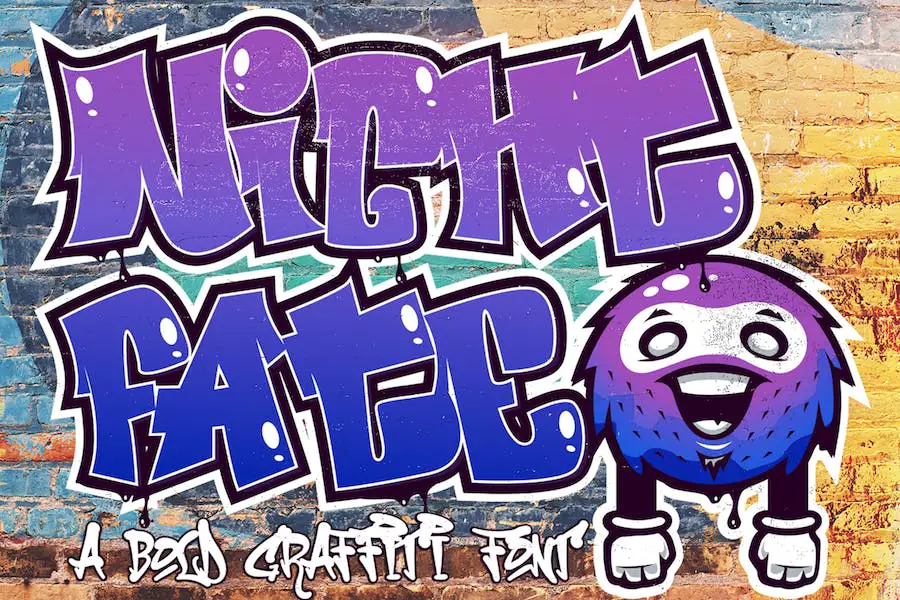
Nightfate 글꼴에서는 특이한 그래피티 같은 모양과 눈에 띄고 프로젝트의 매력을 높일 수 있는 독특한 스타일을 결합하여 프로젝트에 독특한 터치를 추가할 수 있습니다. 그것의 많은 용도 중에는 의류 디자인, 광고, 벽 장식, 공예 등이 있습니다.
Nightfate의 눈에 띄는 특징 중 하나로, 보는 사람의 시선을 확실히 사로잡는 대담하고 엣지 있는 모습은 가장 매력적인 특징 중 하나입니다. 또한 프로젝트 요구 사항과 관련하여 다재다능하기 때문에 이 글꼴을 다양한 용도로 사용할 수 있습니다.
디자인을 한 단계 업그레이드하려는 경우 Nightfate 글꼴을 고려해 볼 가치가 있습니다. 멋진 모양과 개인화된 느낌을 특징으로 하는 이 글꼴은 보는 사람에게 깊은 인상을 남길 것입니다. 시도해 보고 다음 프로젝트의 품질을 어떻게 높일 수 있는지 확인하는 것이 좋지 않습니까?
도시 태그
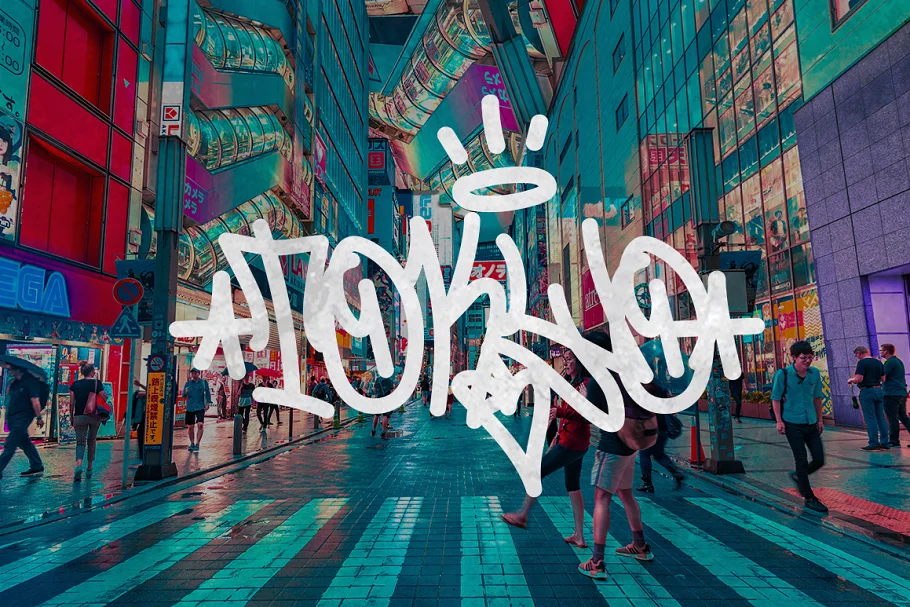
Urban Tags는 그래피티 글꼴로 상징적인 둥근 팁 마커 스타일을 디자인에 적용하여 진정한 스트리트 아트 터치를 선사합니다. 그래피티 씬에 실제 경험이 있는 사람으로서 이 글꼴은 태깅의 본질을 완벽하게 포착했다고 말할 수 있습니다.
Urban Tag를 독특하게 만드는 것은 짧은 공백 문자로 그래피티 스타일의 사실성을 향상시킵니다. 커닝은 일반 글꼴처럼 설정할 수 없으므로 최상의 결과를 얻으려면 커닝을 수동으로 조정해야 합니다. 그러나 최종 결과를 보았을 때 그 노력은 그만한 가치가 있기 때문에 단념하지 마십시오.
이 글꼴은 포스터 및 소품과 같은 디자인 프로젝트에 힙합 또는 거리 예술 감각을 추가하는 데 적합합니다. 엣지있는 음악 앨범 커버부터 도시적인 패션 브랜딩까지 다양한 세팅에 활용될 만큼 활용도가 높습니다. 당신은 문신 예술의 팬입니까? 그렇다면 문신에 그래피티 글꼴을 사용했는지 확인할 수 있습니다.
그래피티 어반
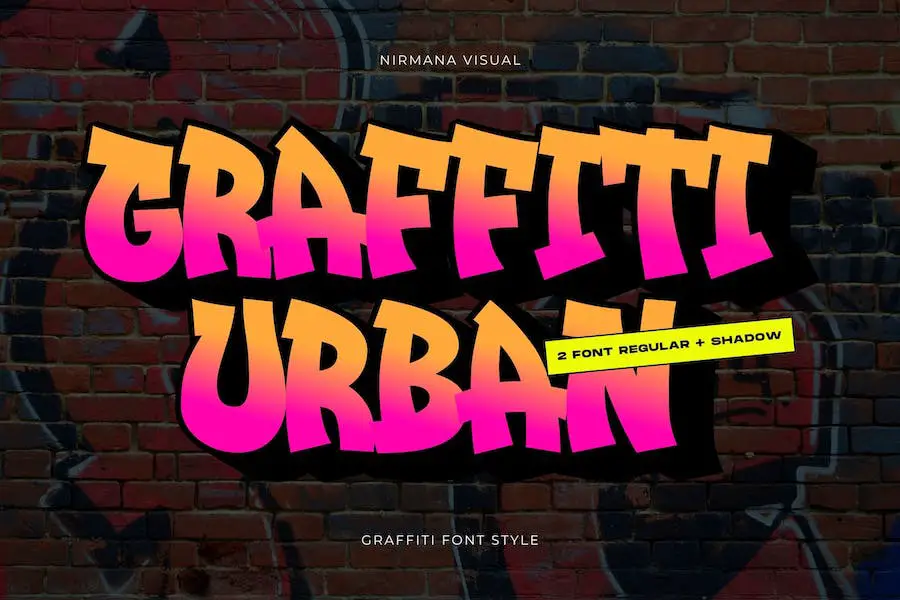
Midbrys 디스플레이 글꼴은 거리 예술 그래피티에서 영감을 얻었으며 멋진 그래피티 글꼴 중 하나입니다. 그렇기 때문에 디자인에 독특한 엣지를 부여하려는 경우 이 서체가 완벽합니다.
Midbrys 글꼴로 대소문자, 숫자, 문장 부호를 표시할 수 있을 뿐만 아니라 다양한 디자인에 쉽게 통합할 수 있어 활용도가 높습니다. 다양한 유형의 디자인 프로젝트도 있습니다.
미드브리스
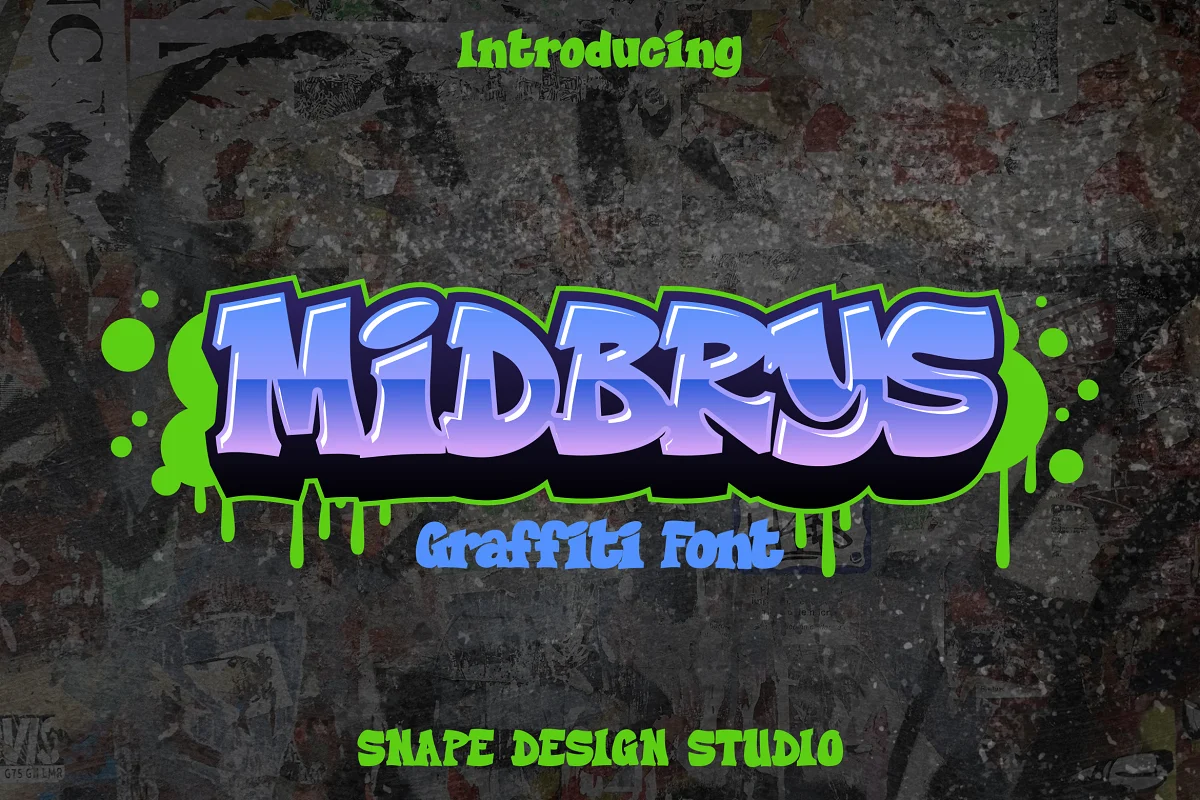
단순히 다재다능한 것 외에도 Amaranc는 로고 생성, 잡지 디자인, 소셜 미디어 게시물, 브로셔 및 기타 여러 유형의 프로젝트에 완벽한 세련된 Graffiti 버블 글꼴 중 하나입니다. Graffiti 글꼴은 Wildstyle 텍스트에도 적합합니다.
대문자, 분음 기호 및 구두점을 특징으로 하는 Amaranc는 읽기 쉽기 때문에 헤드라인이나 제목에 이상적인 서체입니다. 또한 글꼴은 깔끔한 선으로 인해 메시지를 명확하고 효과적으로 전달하는 데 적합합니다.
아마랑
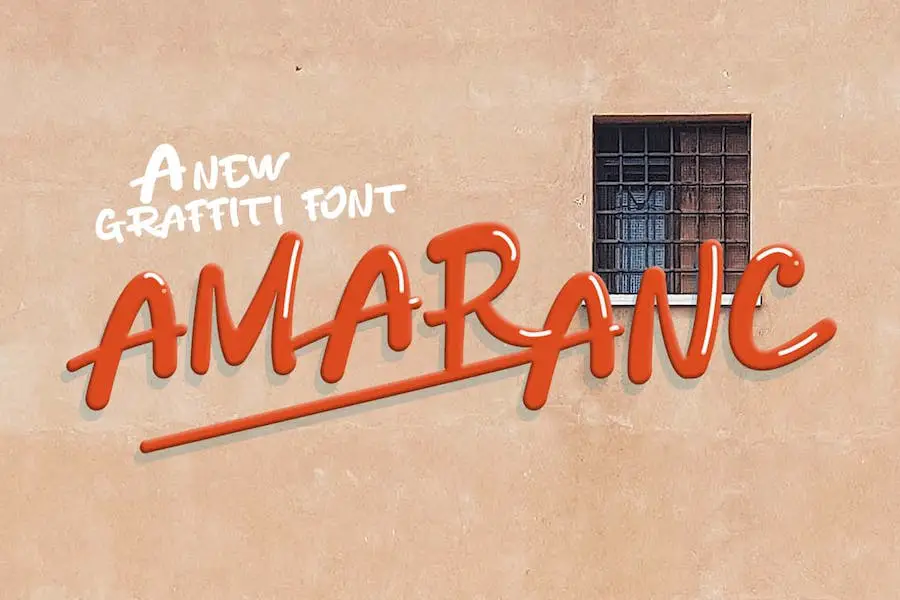
단순히 다재다능한 것 외에도 Amaranc는 브로셔, 로고, 잡지 디자인, 소셜 미디어 게시물 및 기타 여러 유형의 프로젝트를 만드는 데 완벽한 세련된 Graffiti 버블 글꼴 중 하나입니다. Graffiti 글꼴은 Wildstyle 텍스트에도 적합합니다.
대문자, 분음 기호 및 구두점을 특징으로 하는 Amaranc는 읽기 쉽기 때문에 헤드라인이나 제목에 이상적인 서체입니다. 또한 글꼴은 깔끔한 선으로 인해 메시지를 명확하고 효과적으로 전달하는 데 적합합니다.
루저
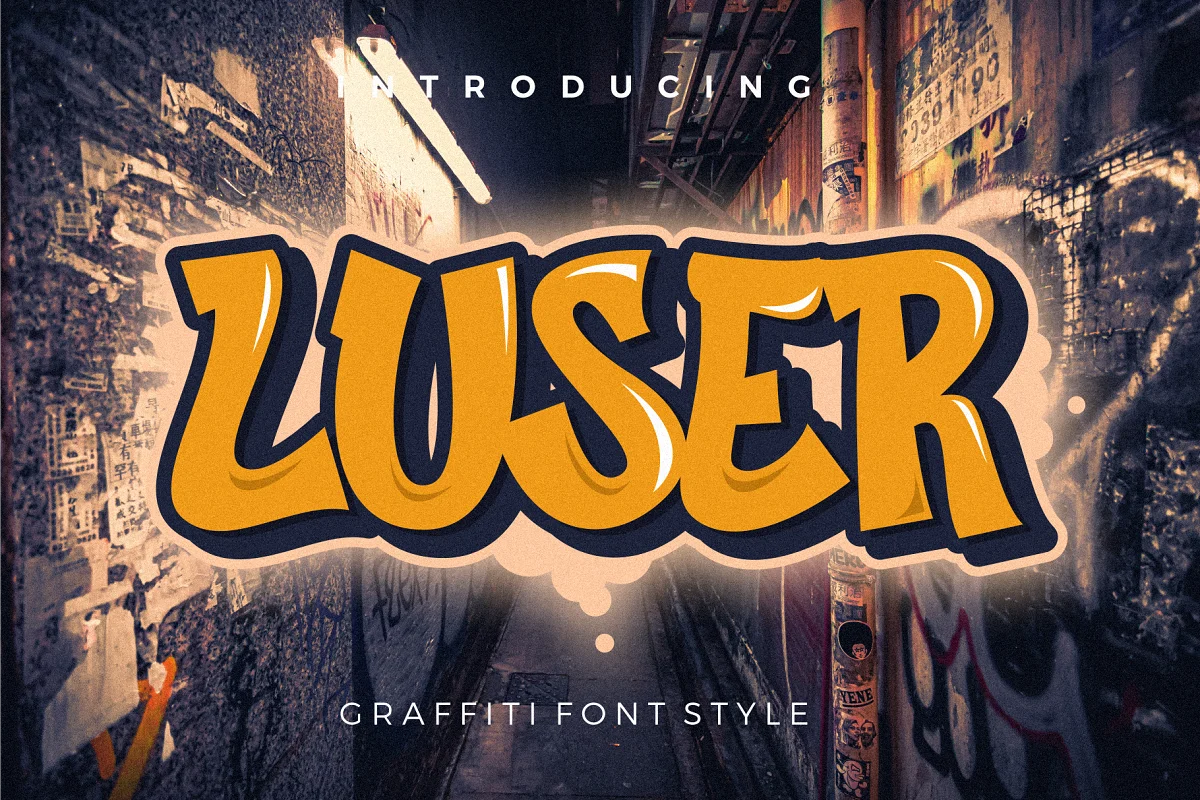
Luser는 힙합 문화와 그래피티의 활기차고 표현력이 풍부한 스트리트 아트에서 영감을 얻은 글꼴입니다. 이 글꼴은 모든 디자인 프로젝트에 도시적인 감각을 더할 수 있는 독특한 기회를 제공합니다.
Luser를 사용하면 디자이너는 쉽게 프로젝트를 향상시키고 타이포그래피에 약간의 개성을 더할 수 있습니다. 엣지 있는 포스터를 만들든 대담한 로고를 디자인하든 Luser는 모든 창의적 요구를 충족할 수 있는 다재다능함을 갖추고 있습니다. Graffiti 글꼴은 그래픽 디자인 및 아트용으로 만들어졌습니다.
로스돌
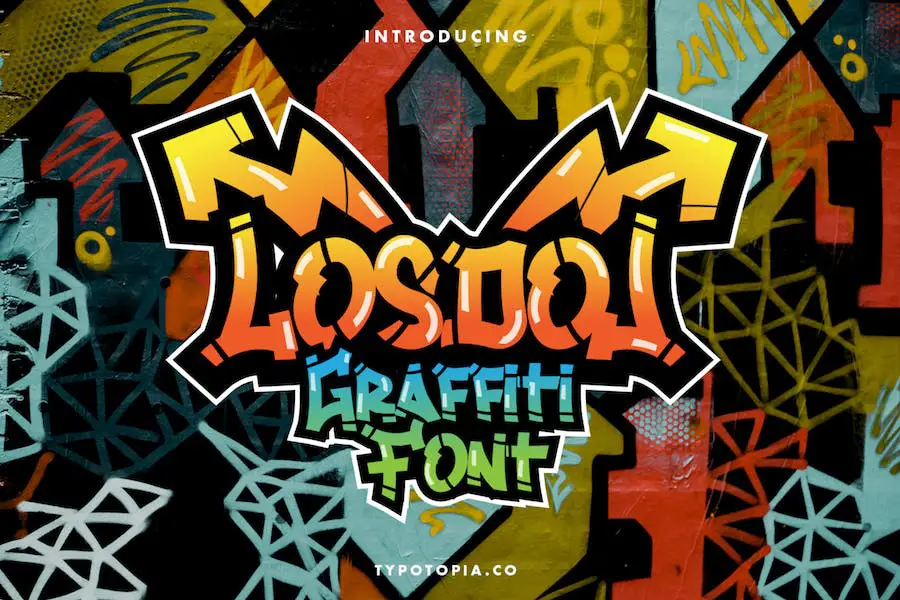
우리 글꼴 패밀리에 가장 최근에 추가된 로스돌 – 그래피티 글꼴을 소개하게 되어 기쁩니다. 이 글꼴은 작품에 엣지와 도시적인 느낌을 더할 글꼴을 찾는 디자이너에게 완벽한 선택입니다.
또한 이 글꼴은 PC 및 Mac 운영 체제와 호환되므로 모든 디자이너가 사용할 수 있습니다.
거리 전쟁
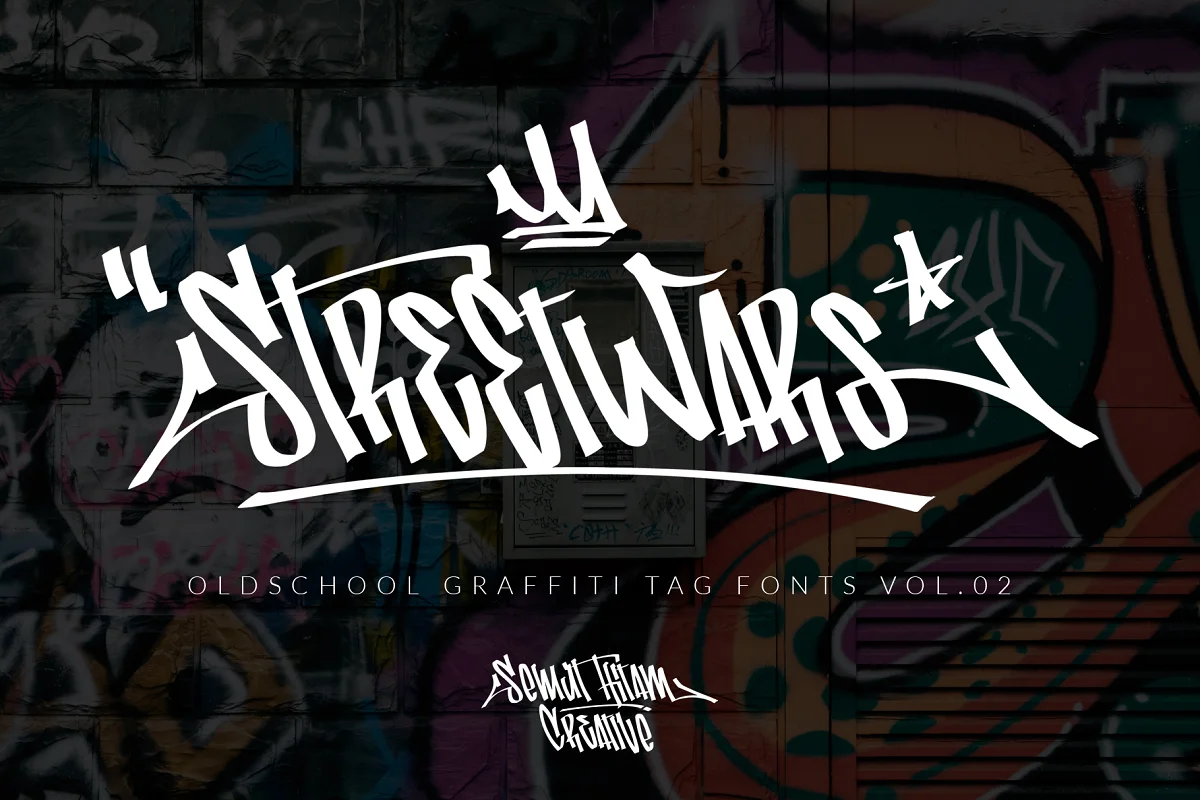
이 빈티지 스타일로 디자인에 펑키한 느낌을 주는 Graffiti Tag Font, Street Wars는 여러분이 찾던 글꼴입니다.
구식 그래피티 태깅에서 영감을 받은 Street Wars는 펑키한 대문자 및 소문자, 숫자, 구두점, 다국어 언어, 문체 스타일 및 다양한 합자를 제공하여 고유한 그래피티 스타일 태그를 만듭니다.
Street Wars의 다양한 기능을 매우 쉽게 혼합하고 일치시켜 나만의 걸작을 만들 수 있습니다. 이 글꼴은 엣지 있는 스트리트 분위기가 가미된 디자인을 만들고자 하는 디자이너에게 매우 적합합니다.
그래피티 라인
Graffiti Line은 도시의 거리에서 볼 수 있는 엣지 있는 그래피티 아트에서 영감을 얻은 디스플레이 글꼴입니다. 이 글꼴을 사용하면 자신만의 그래피티 스타일의 글이나 디자인을 쉽게 만들 수 있습니다. 이 글꼴에는 작업에 멋진 수준을 추가하는 다양한 합자가 함께 제공됩니다.
이 스타일의 아트워크는 다양한 디자인 프로젝트, 포장, 로고, 월 아트, 헤드라인, 템플릿, 다양한 배너, 포스터 등과 잘 어울립니다.
이 글꼴은 다양한 언어로 사용할 수 있어 전 세계 사람들이 어디에 있든, 어떤 민족에 속해 있든 상관없이 사용할 수 있기 때문에 오늘날 가장 인기 있는 글꼴 중 하나입니다.
식스3
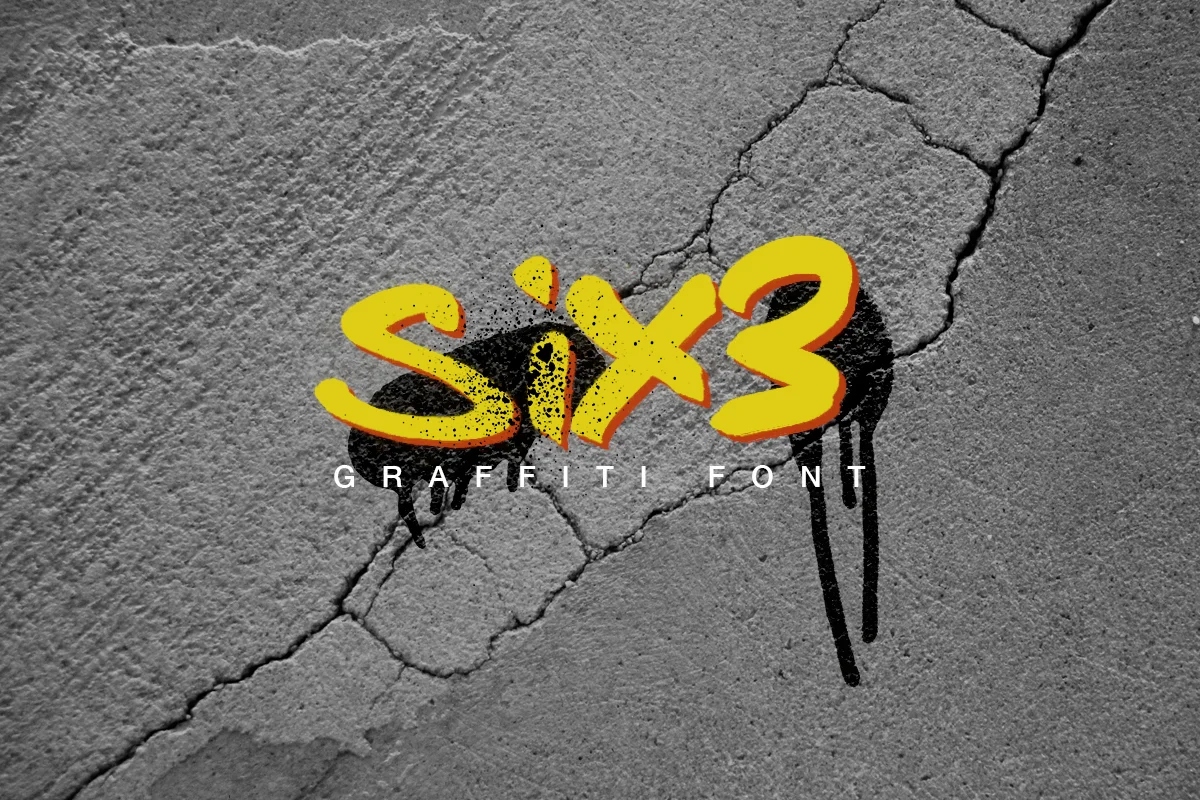
Six3와 같은 멋진 도시형 그래피티 글꼴보다 더 트렌디하고 신나는 것은 없습니다. 이 글꼴은 매우 세련되고 도시적이어서 작업 라인에 개성과 거리 예술을 추가하고자 하는 모든 그래픽 디자이너의 요구를 충족할 수 있습니다.
Six3 글꼴은 전통적인 그래피티 태그를 연상시키는 대담하고 굵은 선이 특징입니다. 글자는 의도적으로 고르지 않고 약간 왜곡되어 생생하고 진정한 느낌을 줍니다. 이 글꼴은 대문자와 소문자로 사용할 수 있어 다양한 디자인 요구 사항에 대한 유연성을 제공합니다.
디스트릭트사이드
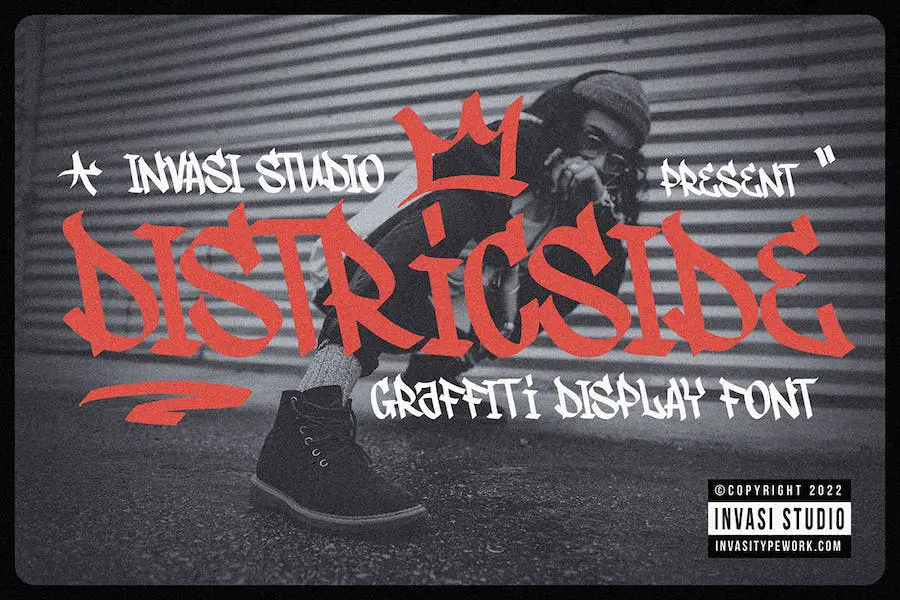
현재 사용 가능한 그래피티 글꼴이 많이 있지만 Districtside는 도시 생활 방식에서 영감을 얻은 글꼴입니다. 또한 프로젝트를 시각적으로 더욱 매력적으로 보이게 하는 추가 스와시 글꼴이 포함되어 있습니다.
이 글꼴 스타일은 더 대담하고 읽기 쉽기 때문에 제목, 로고, 제품 포장, 브랜딩 프로젝트, 잡지, 소셜 미디어 및 군중에서 단어가 눈에 띄어야 하는 기타 매체에 적합합니다.
비쉬
BISH는 다양한 디자인 요구에 맞는 6가지 고유한 스타일과 함께 제공되는 인상적인 그래피티에서 영감을 받은 글꼴 모음입니다.
이 글꼴 모음은 프로젝트 디자인을 개선하고 스타일리시한 세부 사항을 추가하여 더 세련된 모양을 제공하려는 그래픽 디자이너에게 적합합니다.